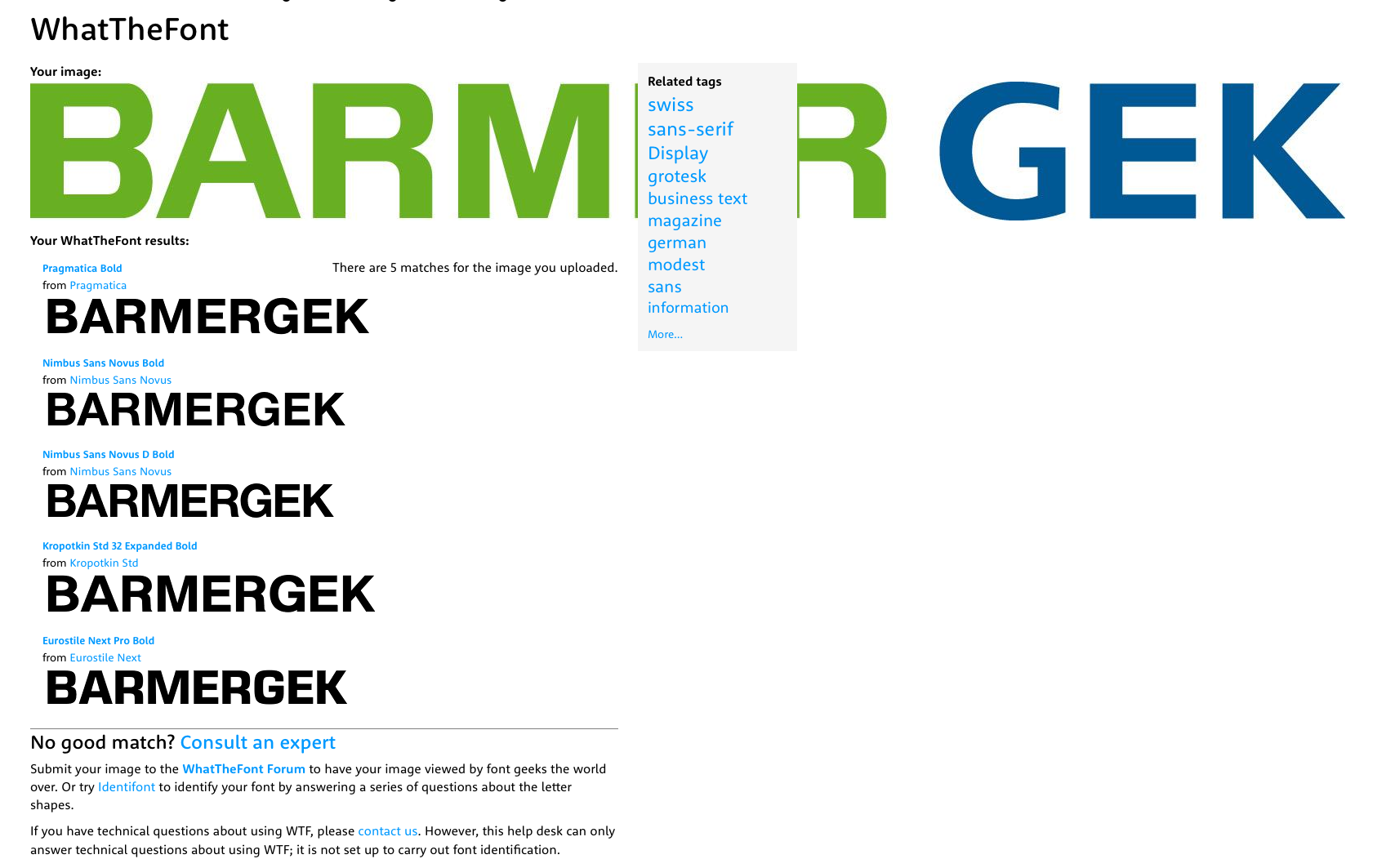
Barmer-GEK-Schrift gesucht
das Forum ist echt der Hammer. Was bisher gesuchten Schriften angeht, so konntet Ihr mit immer helfen.
Jetzt stehe ich vor dieser Schrift: siehe Anhang.
Auftraggeber die Barmer verweist auf eine Logodatei als JPEG. Nachbauen kostet zuviel Zeit und krieg ich nicht bezahlt mittels einer Schrift würde ich mir da Abhilfe schaffen.
Whatafont suche brachte auch kein zufriedenstellendes Ergebnis: hab ich Euch auch in den Anhang gepackt.
Ich vermute beide Wortmarken wurden ursprünglich aus einer abgewandelten Schrift erstellt:  »BARMER« ist mit hoher Wahrscheinlichkeit eine angepasste Eurostile, »GEK« geht eher in Richtung Frutiger.
Frage ist schon eine Weile her, fand die passende Schriftart. Sollte die Familie "Titillium" sein.
Die Titillium ist formal doch arg weit entfernt …